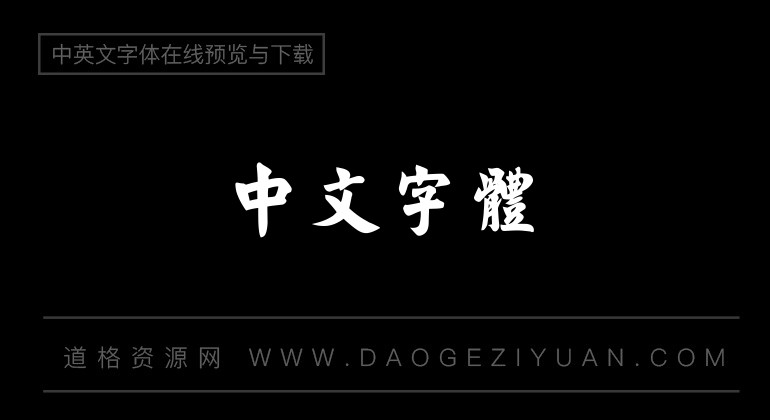
经典繁毛楷
经典繁毛楷是一种繁体字的书法字体,它的特点是毛笔细腻,线条优美,楷书曲折,视觉效果精美。它有着深厚的文化底蕴,书写精美,笔画清晰,结构严谨,给人以舒适的视觉感受,是中国传统文化的缩影。它更加突出了文字的立体感,表达出文字的灵动与细腻,使得书法更加精美。
经典繁毛楷是一款非常不错的手写艺术字体,具有很好的视觉感,适合于文化类的宣传设计、商业类品牌的广告和产品包装设计以及个性化文字排版等较多场景。